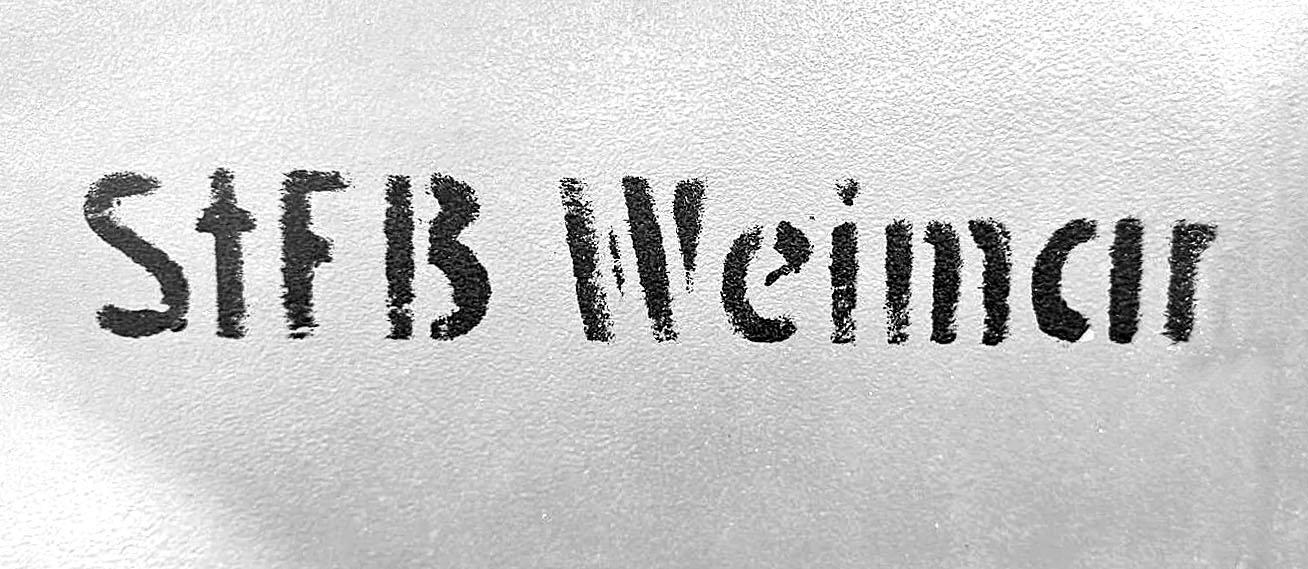
Schablonen Schrift DDR
Ich suche für eine Restauration diese oder eine ähnlichen Schablonen Schrifttyp ( DDR - 70er)
Auf der Mustertafel steht StFB Weimar ( Staatlicher Forst Betrieb)
Gibt es evt. etwas ähnliches? Ich  konnte auch nach langem Suchen nichts finden - auf dem restaurierten Fahrzeug soll zur Fertigstellung  - StFB Neuruppin - stehen.
Bei Schablonenschriften würde ich die Suche bei astype beginnen.